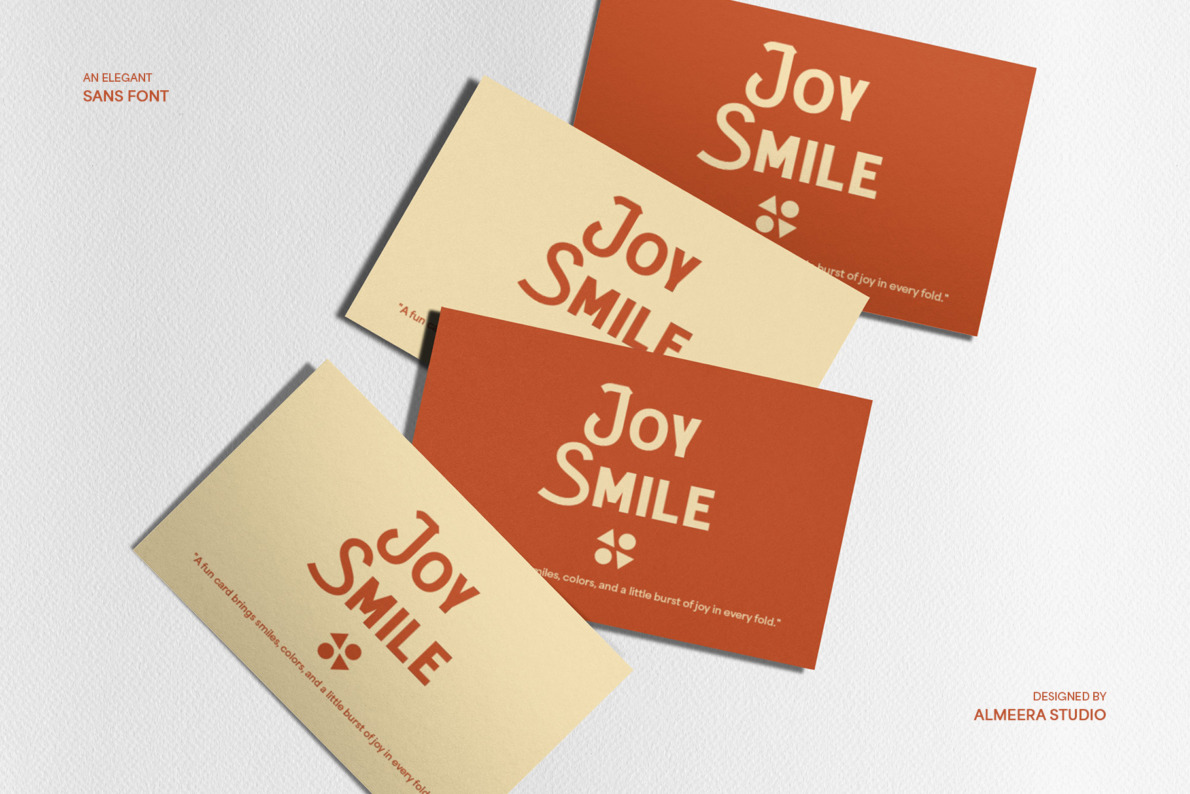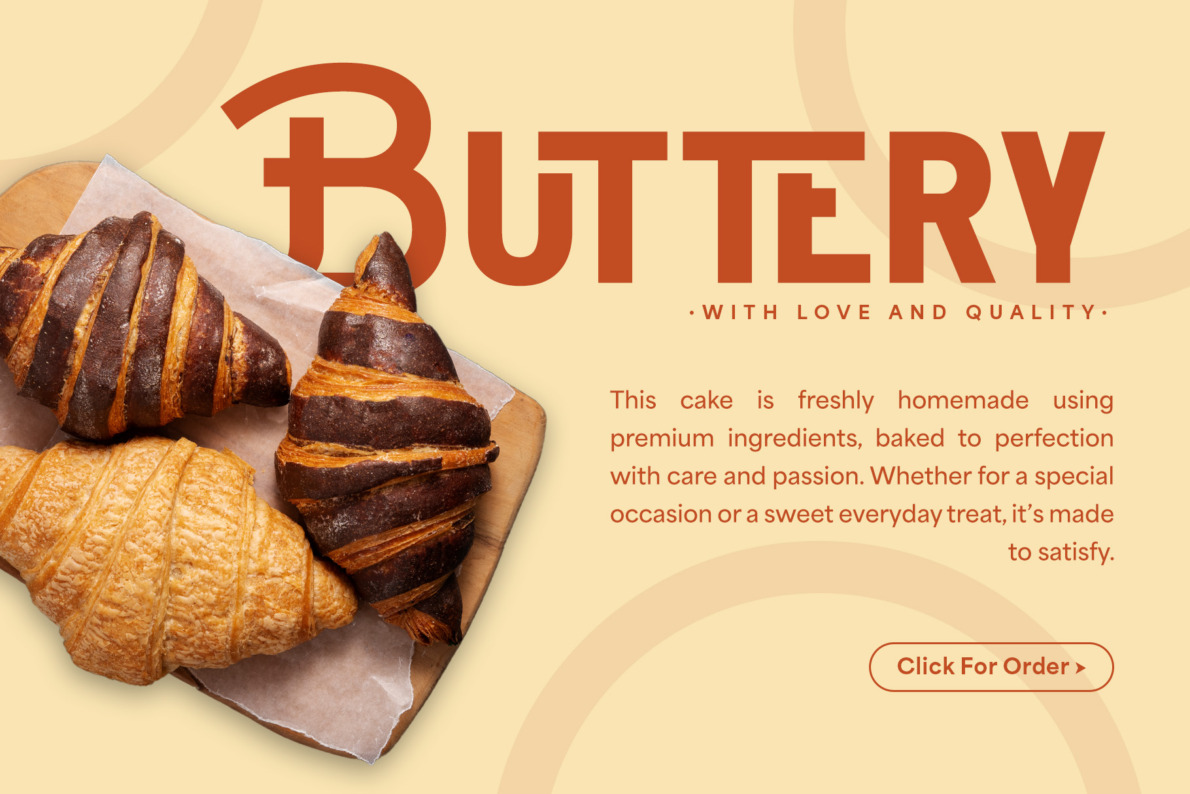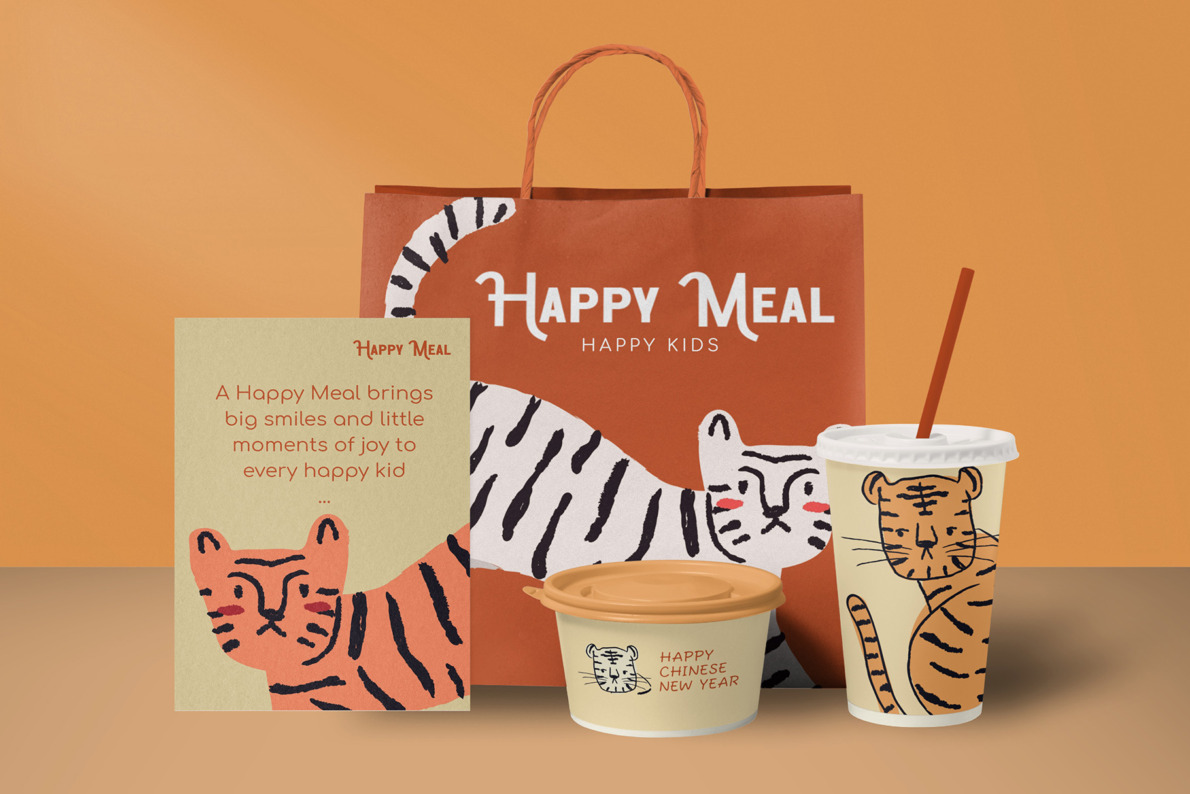
Giới thiệu về Font TF Molare Việt hóa
TF Molare Việt hóa là một font chữ không chân (sans-serif) nổi bật với thiết kế trang trí, độc đáo và đầy cá tính. Font này mang đến vẻ ngoài hiện đại, phóng khoáng nhưng vẫn có sự tinh tế, lý tưởng để tạo điểm nhấn nghệ thuật và thu hút mọi ánh nhìn, đặc biệt trong các lĩnh vực cần sự sáng tạo và khác biệt.
Với đặc điểm thiết kế độc đáo và khả năng tạo ấn tượng mạnh mẽ, Molare là lựa chọn lý tưởng cho các thiết kế muốn truyền tải sự hiện đại, cá tính và phong cách:
• Branding cafe: Hoàn hảo để sử dụng cho logo, bao bì sản phẩm, hoặc các ấn phẩm nhận diện thương hiệu của các quán cà phê hiện đại, đặc biệt là những nơi có phong cách độc đáo, nghệ thuật hoặc thủ công. Font này giúp tạo dựng một hình ảnh thương hiệu mạnh mẽ, dễ nhớ và có gu.
• Thiết kế poster: Lý tưởng để tạo các tiêu đề chính hoặc thông điệp quảng cáo trên poster cho các sự kiện, chương trình khuyến mãi, hoặc các sản phẩm muốn gây ấn tượng thị giác mạnh mẽ.
• Name card: Phù hợp để sử dụng trên danh thiếp, mang lại vẻ ngoài chuyên nghiệp, hiện đại và độc đáo, giúp tạo ấn tượng khó quên với đối tác hoặc khách hàng.
• Thiết kế bao bì sản phẩm: Có thể dùng cho các sản phẩm thủ công, đặc sản địa phương, hoặc các mặt hàng muốn truyền tải sự độc đáo và chất lượng.
Với TF Molare Việt hóa, bạn có thể dễ dàng thổi hồn sáng tạo, sự độc đáo và cá tính vào các thiết kế, tạo ra những sản phẩm không chỉ đẹp mắt mà còn cực kỳ ấn tượng và có khả năng thu hút sự chú ý tối đa.